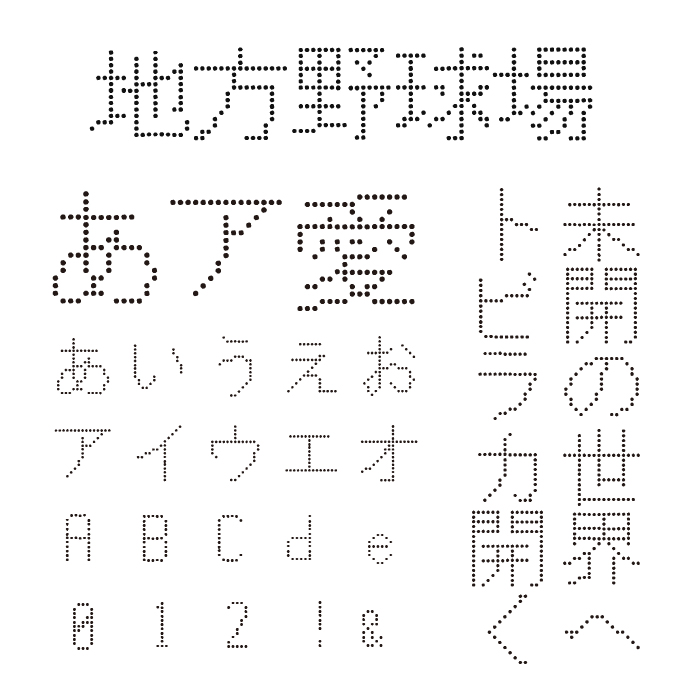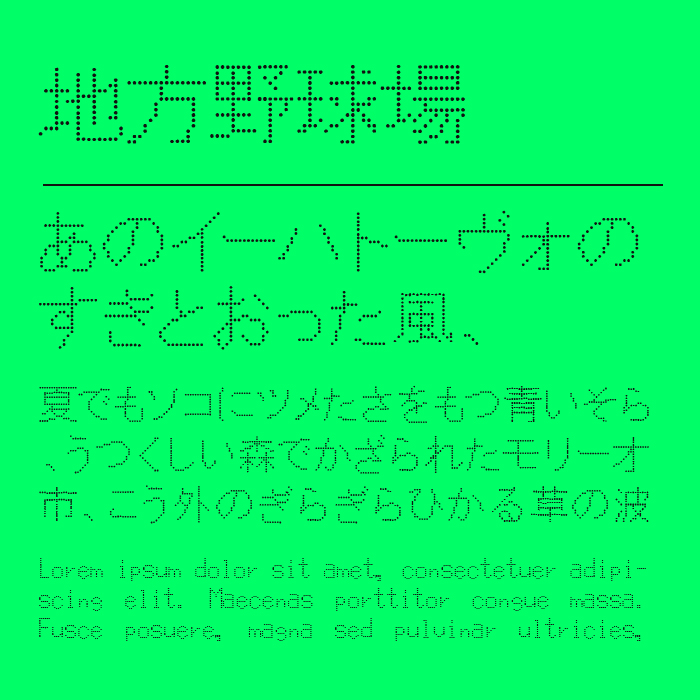
地方野球場電光掲示板フォントは、ドットで構成されたユニークなデザインフォントです。
80年代神宮球場や地方野球場の電光掲示板のイメージして制作されているため、懐かしい電光掲示板やLEDのような質感が特徴で、どこかレトロで昭和的な雰囲気を漂わせています。文字が点で描かれているため、遠目に見ると独特の表情を持ちます。
掲示板や野球スコアボード、ゲームUIのようなシーンに使うことで、懐古的かつインパクトのある表現できました。昭和レトロ・野球・電光掲示板などのキーワードにぴったりなフォントです。